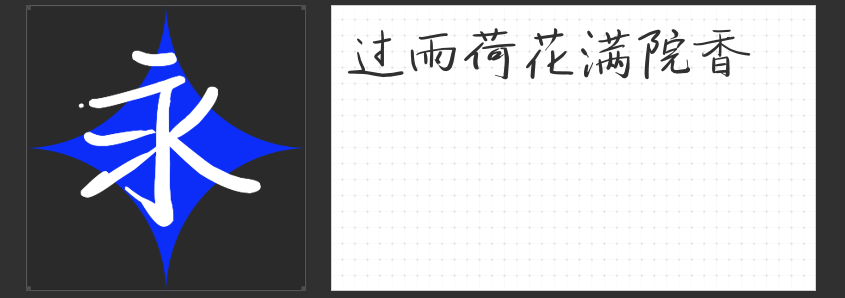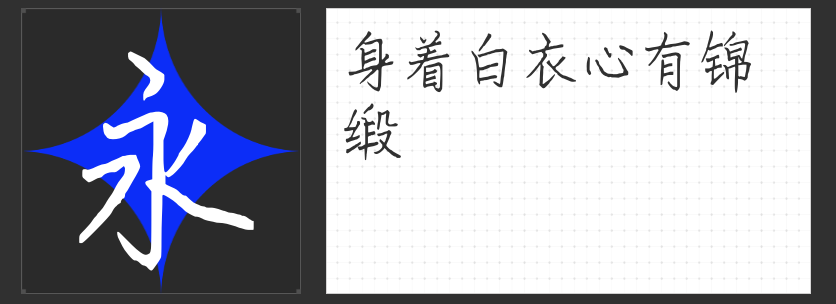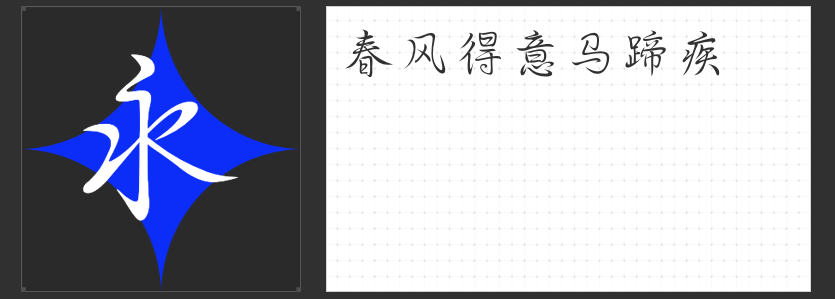
楷书之韵:四款精选楷书字体推荐
在书法的世界里,楷书以其端庄、秀丽、严谨的结构,成为了众多书法爱好者的首选。今天,我们将为大家推荐四款各具特色的楷书字体,让我们一起领略它们的独特魅力。
1.云书法玉兰行楷体
这款字体融合了楷书的稳重与行书的流畅,笔画细腻,字形优雅,如同玉兰绽放,散发着淡淡的清香。它适用于诗词、散文等文艺作品的排版,能够增添一份清新脱俗的气质,让读者在享受文字之美的同时,也能感受到一份宁静与和谐。
这款字体以其粗犷而不失规矩的特点,赢得了众多设计师的喜爱。笔画粗犷有力,结构紧凑,给人一种强烈的视觉冲击力。它适合用于标题、海报等需要强调力量感和视觉焦点的设计,能够迅速吸引观者的目光,传递出作品的独特风格。
这款字体则以其温婉细腻、含蓄内敛的风格,赢得了不少人的青睐。笔画柔和,字形圆润,如同春风拂面,给人一种温暖而舒适的感觉。它适用于散文、小说等文学作品的排版,能够营造出一种温馨、宁静的阅读氛围,让读者在享受文字的同时,也能感受到一份心灵的慰藉。
这款字体则以其硬朗、挺拔的笔画,展现出了楷书的力量之美。字形方正,结构严谨,给人一种稳重而坚定的感觉。它适合用于公文、报告等正式文件的排版,能够彰显出文件的权威性和专业性。
总之,这四款楷书字体各有千秋,无论是追求优雅、粗犷、温婉还是硬朗,都能在其中找到心仪的选择。让我们一起在楷书的世界里,感受文字的魅力,品味生活的韵味。